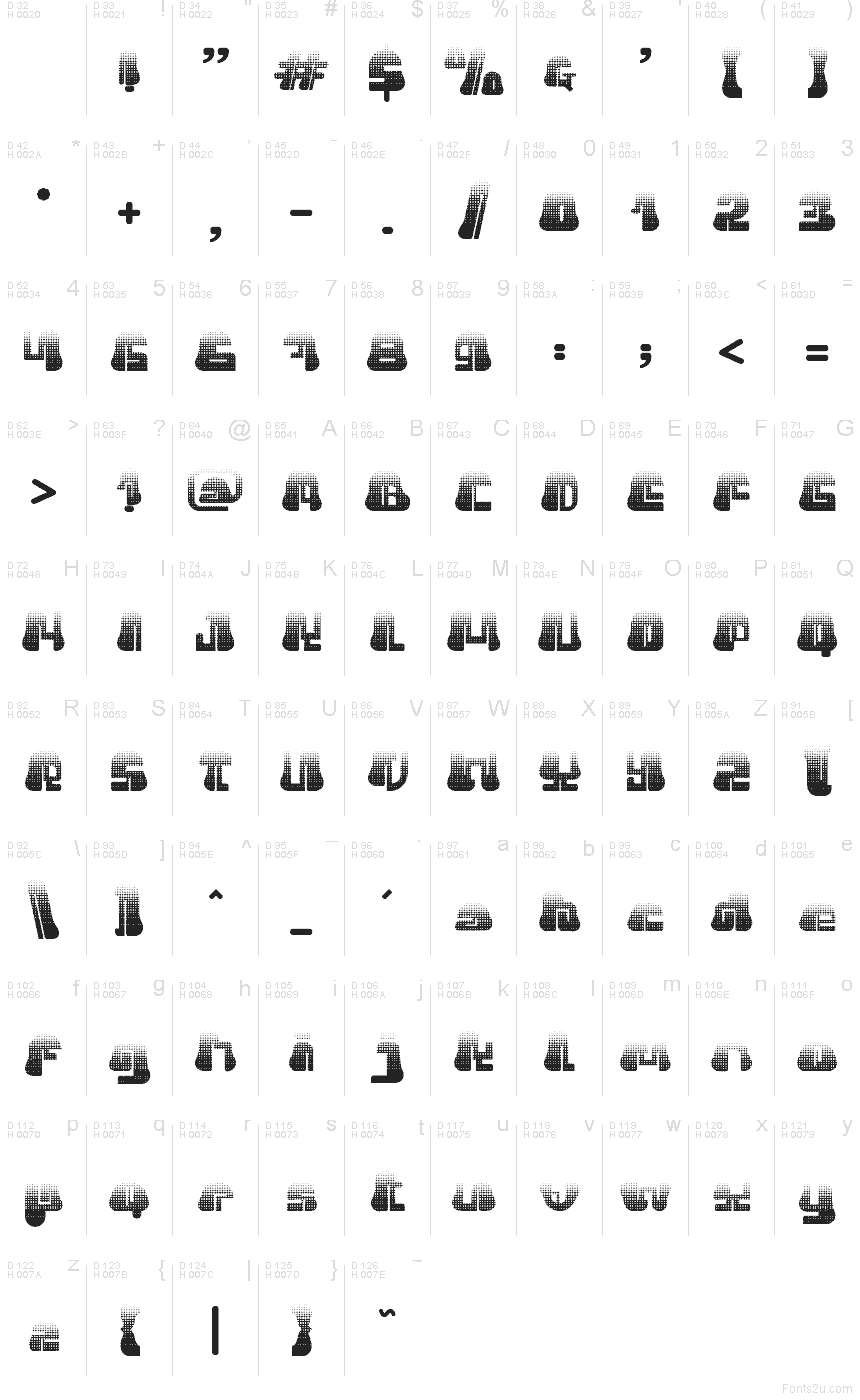
Vibe Tribe Six de Putracetol Studio es una tipografía display gratuita de aire setentero y aspecto desgastado, con letras abultadas y redondeadas que evocan la marcada silueta de los carteles de los años 70. Densas tramas de semitonos recorren las formas, dividiendo las zonas sólidas en bandas de textura y aportando a las curvas amplias una superficie serigrafiada y ligeramente envejecida.
Su carácter psicodélico retro se adapta muy bien a carteles musicales y gráfica para festivales, gracias a una rotulación con patrones que puede integrarse en la propia obra gráfica. También encaja a la perfección en portadas de discos y marcas de streetwear. Su público predilecto son diseñadores que trabajan con la cultura de club vintage, el funk o identidades de marca nostálgicas y desenfadadas.